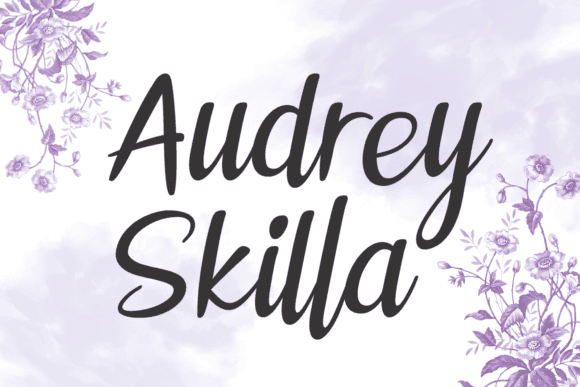
Fuente Audrey Skilla para manualidades, logotipos y proyectos de impresión
Audrey Skilla es una tipografía impactante que personifica la gracia, la belleza y la sofisticación. Diseñada con meticulosa atención al detalle, esta fuente irradia un aura de elegancia y encanto, lo que la convierte en la opción ideal para proyectos que requieren un toque de refinamiento y lujo. Crea invitaciones de boda impactantes, tarjetas de reserva de fecha y notas de agradecimiento que derrochan romance y sofisticación.
- Diseño elegante y agraciado
- Perfecto para invitaciones de boda.
- Añade un toque de lujo a cualquier proyecto.
Fuente Audrey Skilla: una tipografía elegante y sofisticada